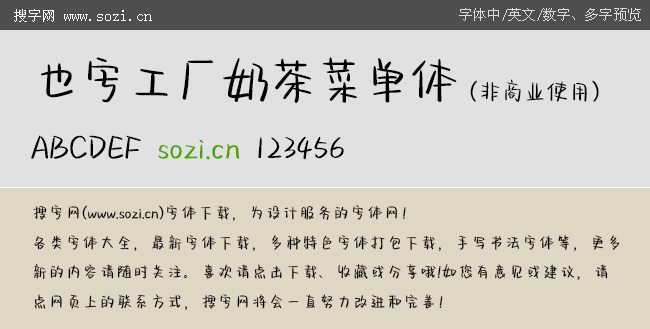
也字工廠(chǎng)奶茶菜單體
搜字網(wǎng)給大家提供一款也字工廠(chǎng)奶茶菜單體(非商業(yè)使用)中文字體下載,也字工廠(chǎng)奶茶菜單體是一款手寫(xiě)書(shū)法字體,字體書(shū)寫(xiě)流暢,自然大方,具有很好的視覺(jué)效果。適合應(yīng)用于書(shū)籍畫(huà)冊(cè)、海報(bào)、網(wǎng)頁(yè)設(shè)計(jì)等應(yīng)用(此字體為個(gè)人非商用版,商用可以聯(lián)系:官方網(wǎng)址:https://yefont.com/home,聯(lián)系方式:13798980448)。